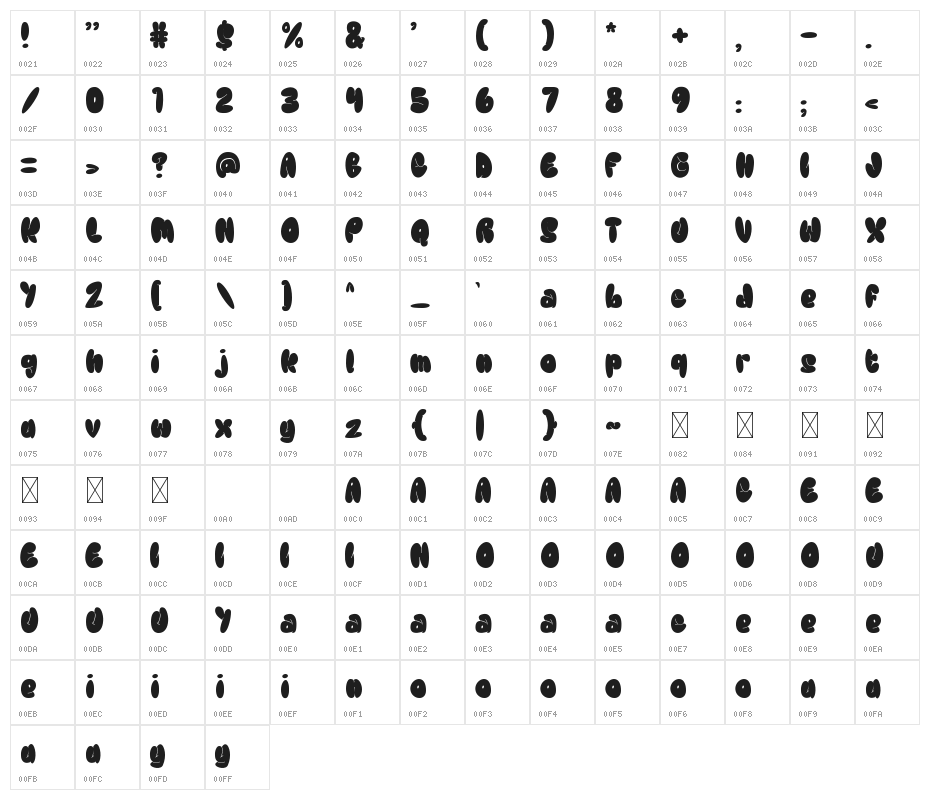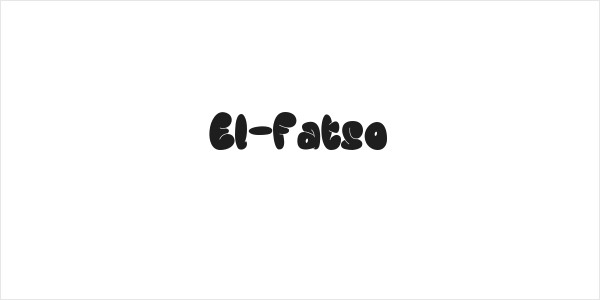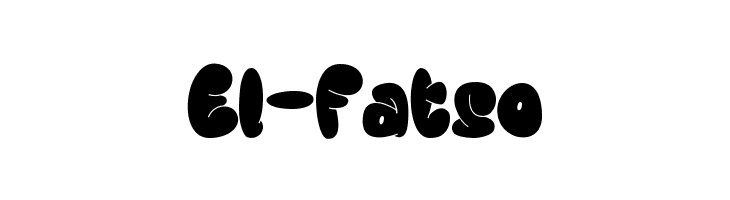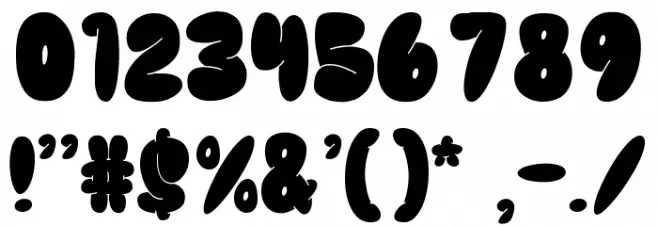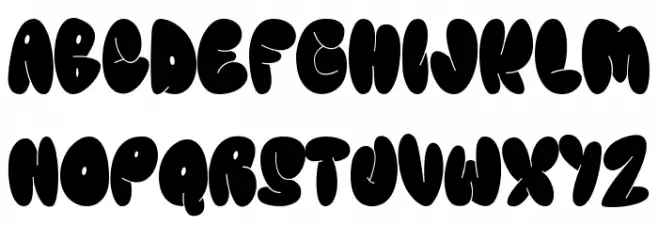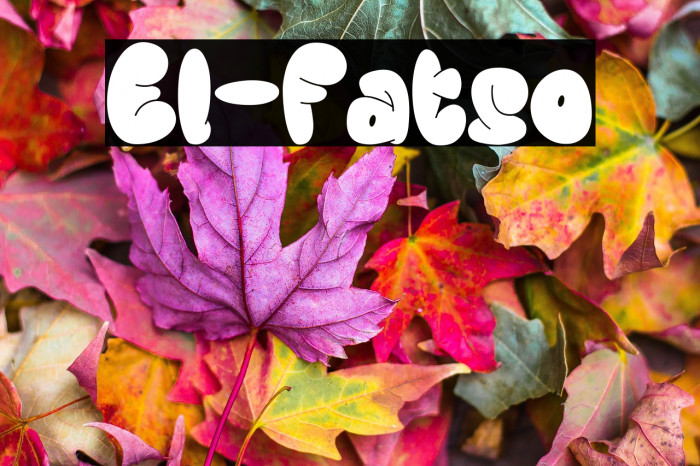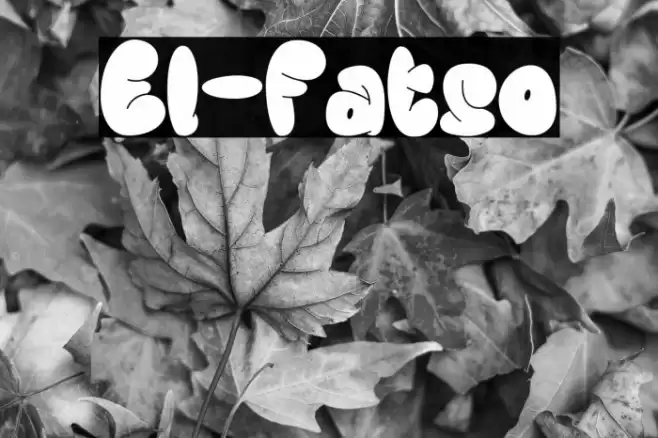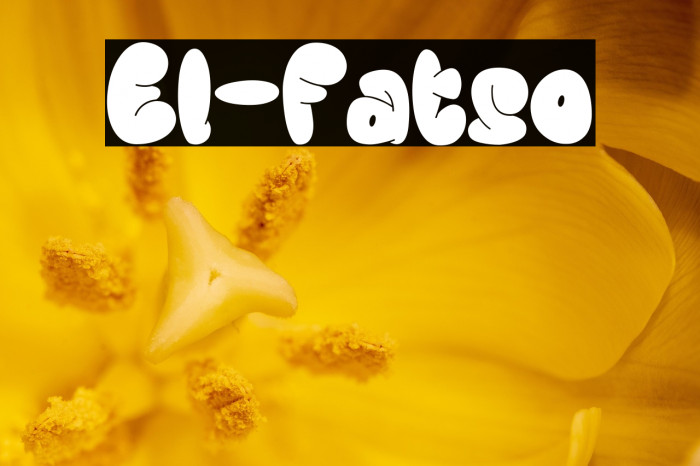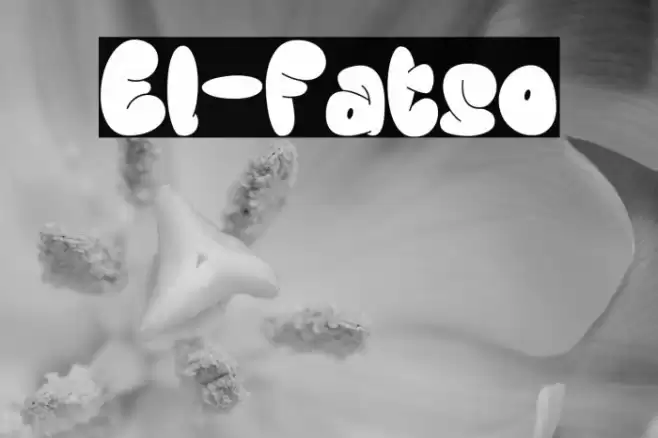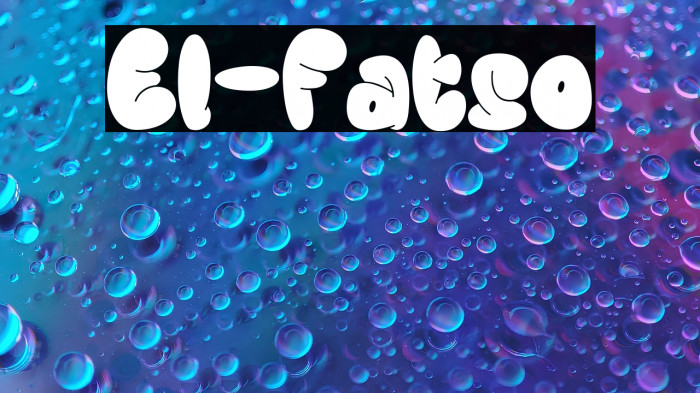
El-Fatso Font
| Gesamtstil | Playful |
| Anwendungsfall | Logos, Headlines, Posters |
| Vorgeschlagene Projekte | Ideal for children's books, playful branding, party invitations, and eye-catching posters. |